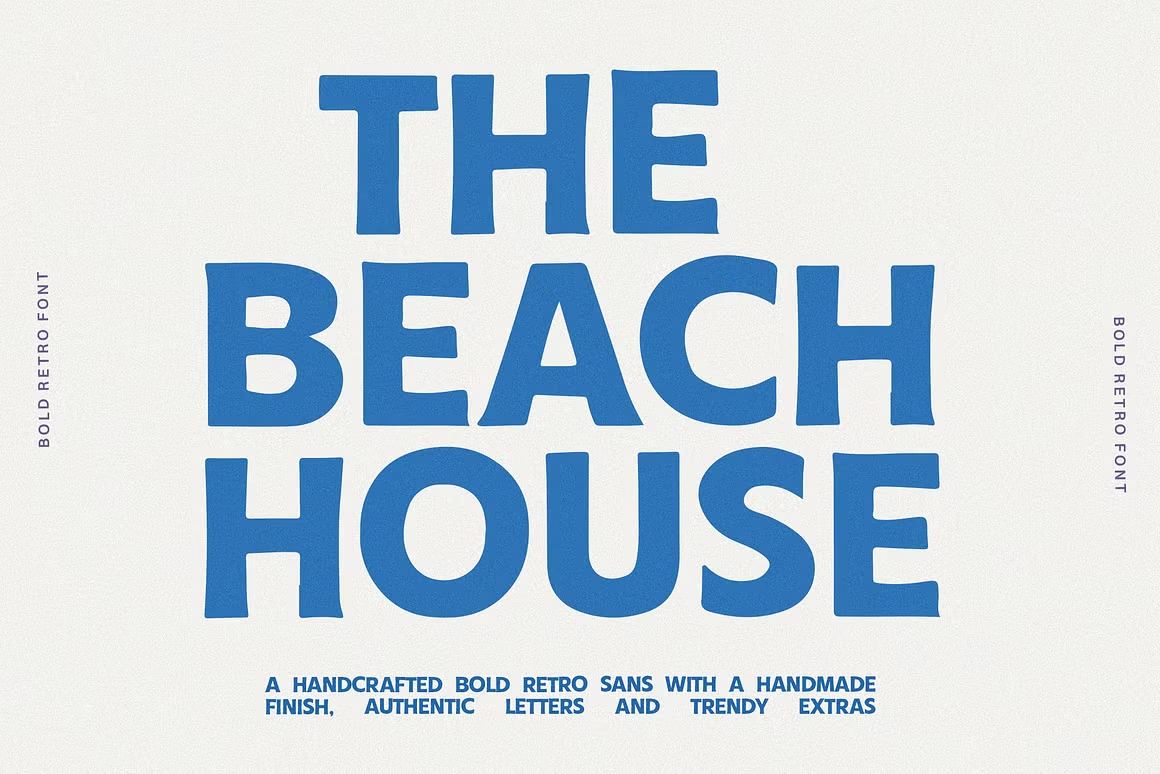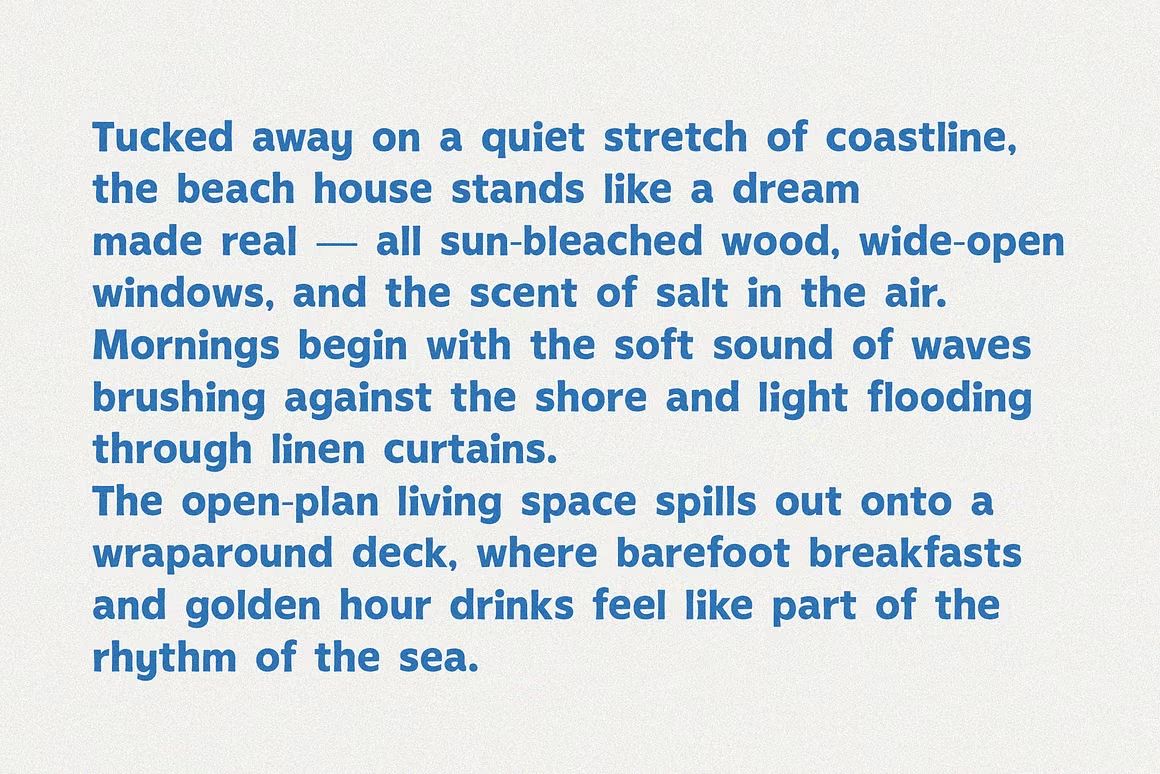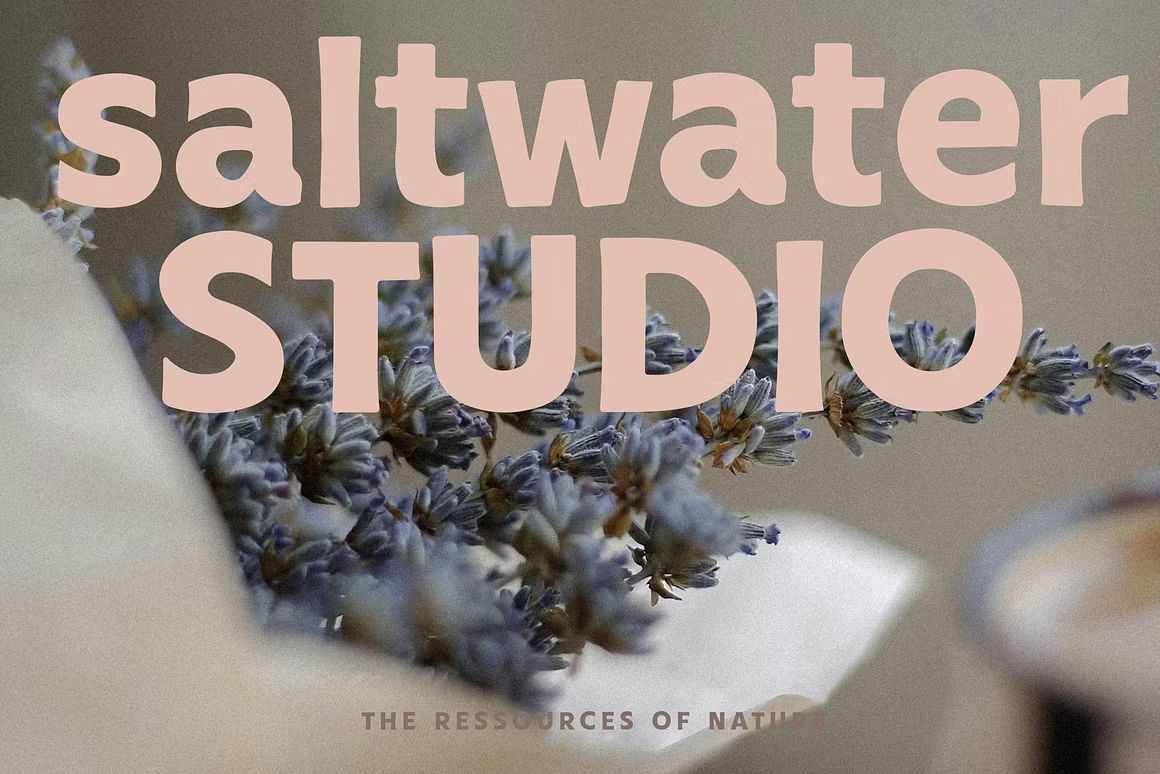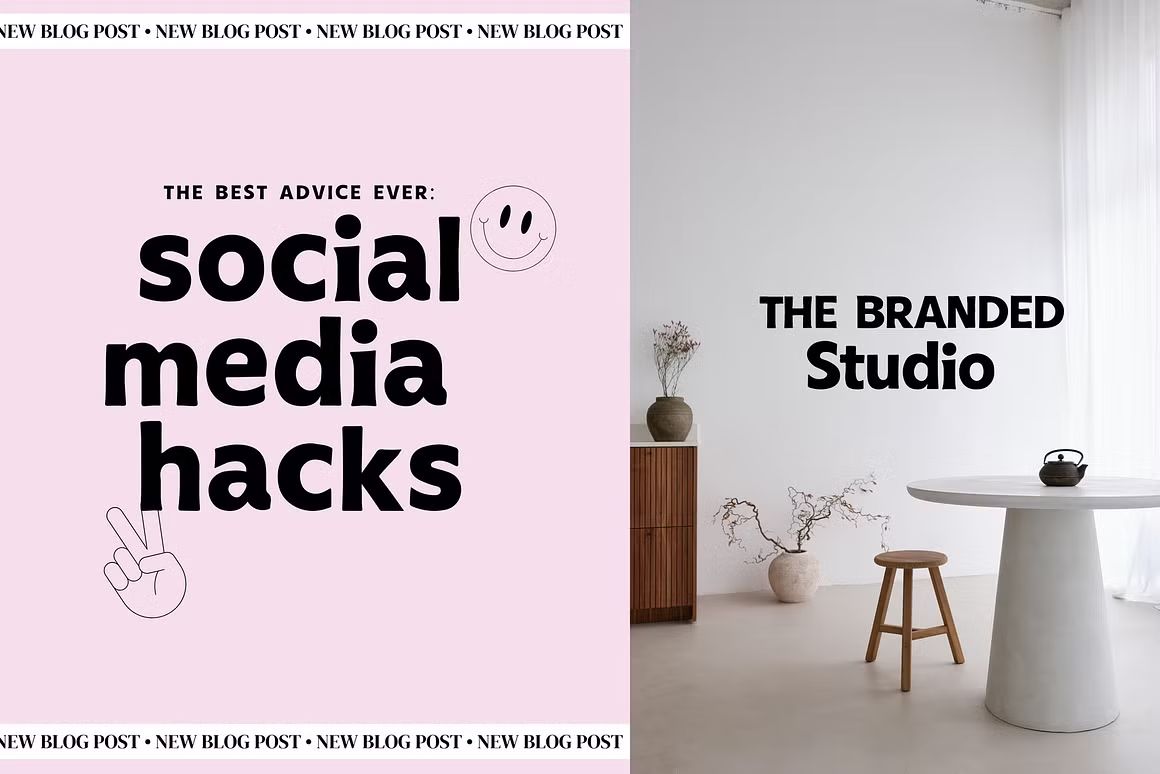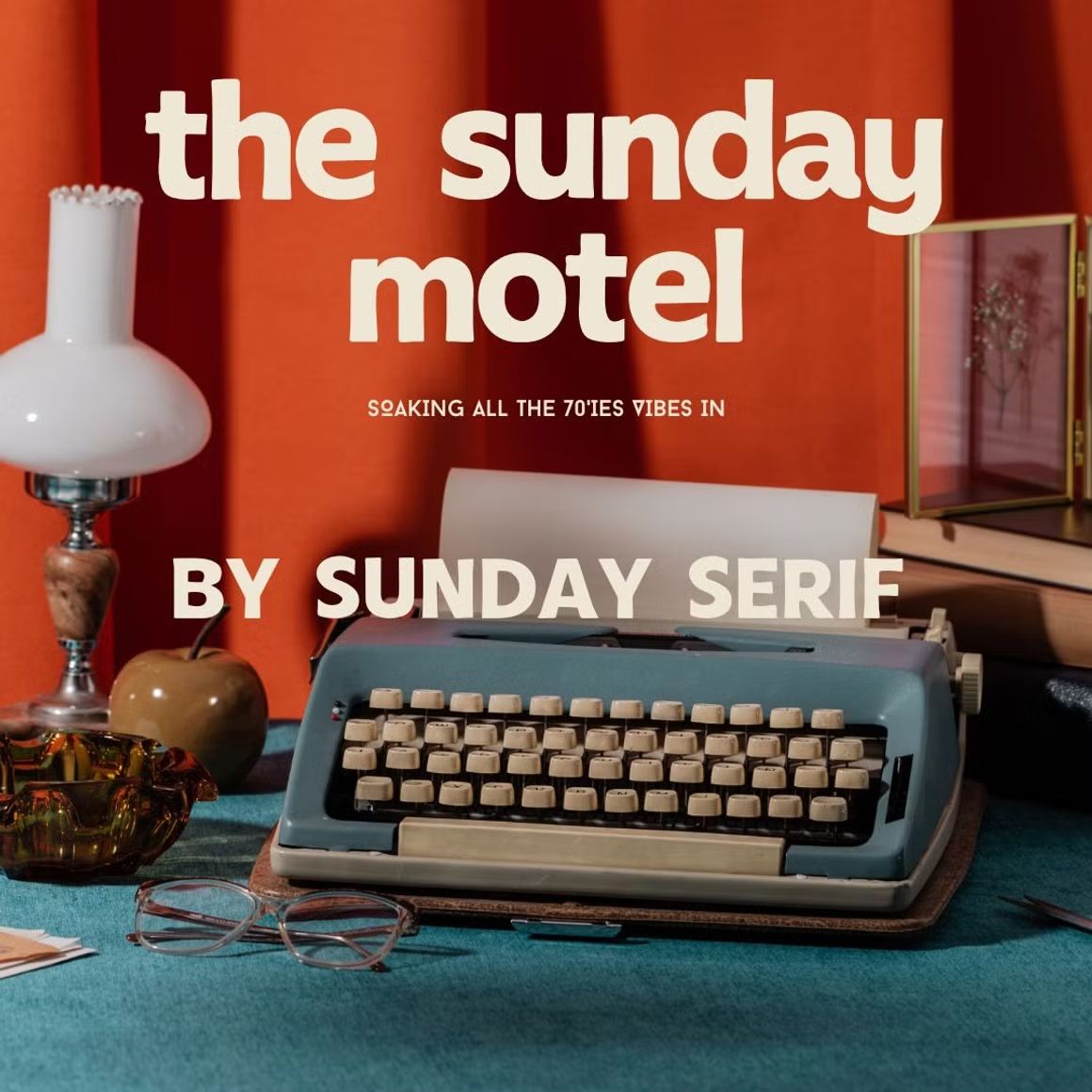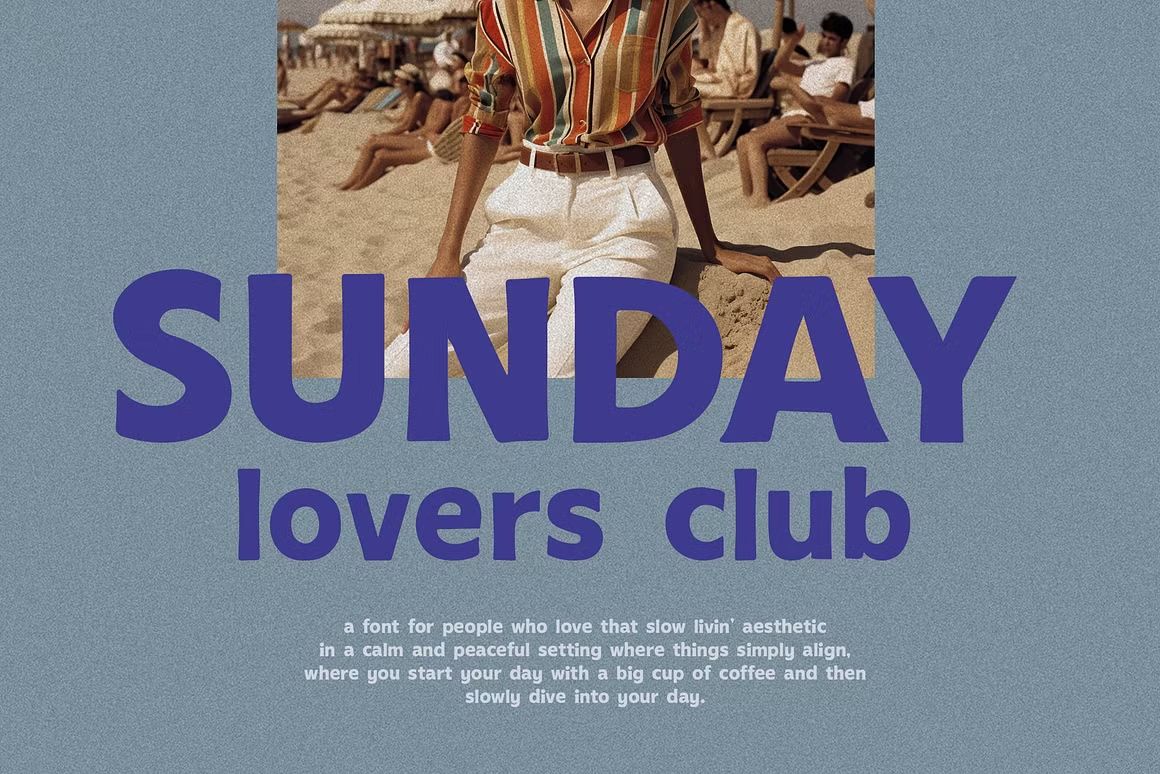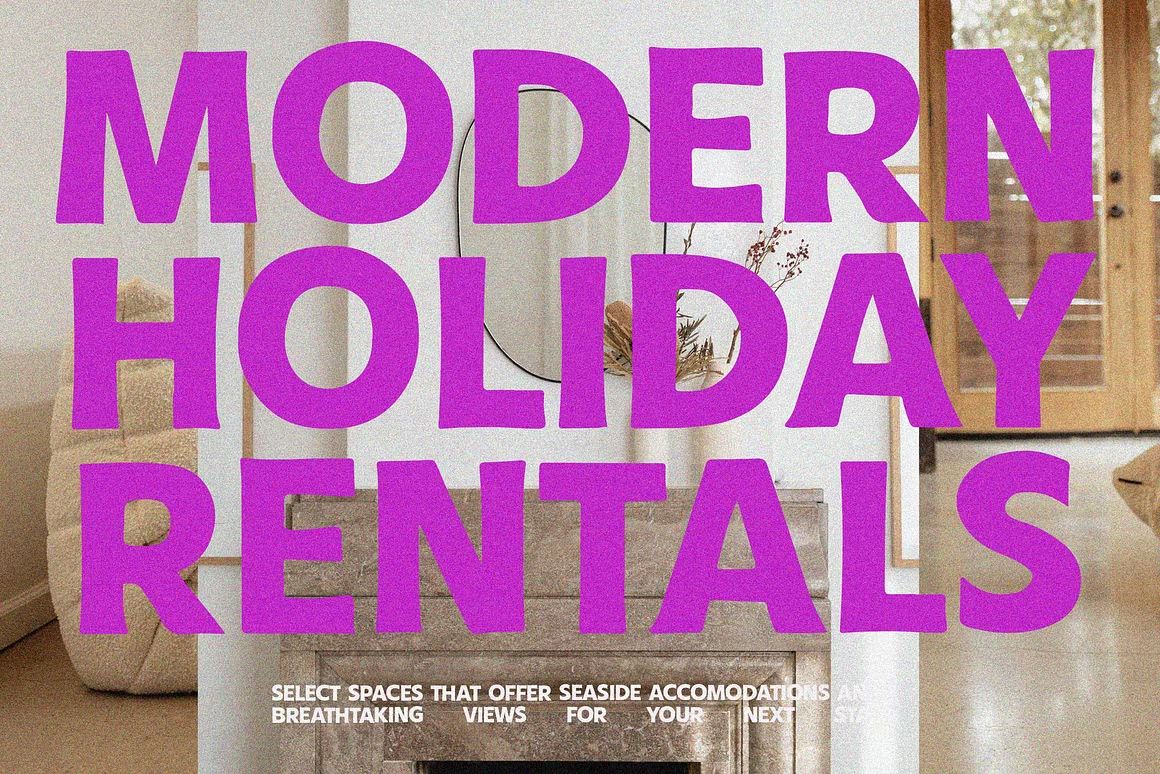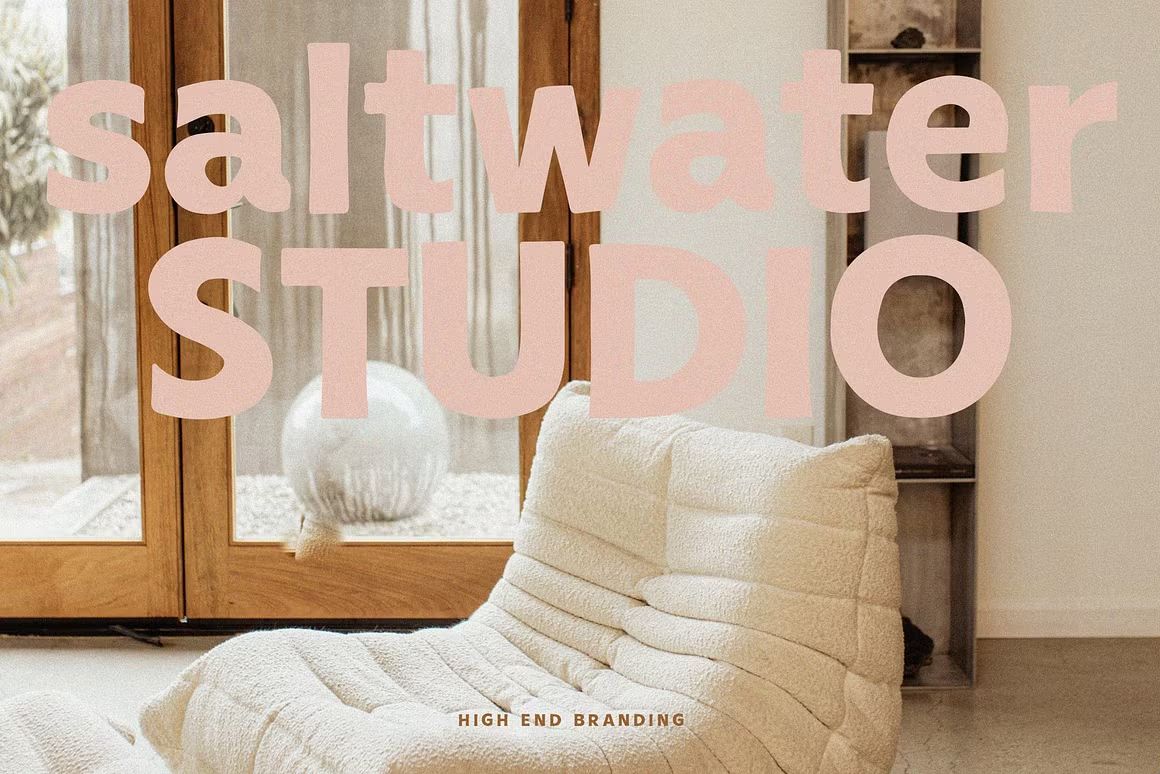
Beach House – Bold Sans Serif Font
Beach House adalah font sans serif tebal dengan gaya modern dan kasual, cocok untuk desain poster, branding, kemasan, dan proyek kreatif yang ingin tampil mencolok dan santai.
Beach House adalah font sans serif bold dengan tampilan modern dan kasual yang dirancang untuk menarik perhatian. Dengan bentuk huruf yang kuat dan bersih, font ini sangat cocok digunakan untuk poster, branding, kemasan produk, dan berbagai proyek desain yang ingin menonjolkan kesan santai namun tetap profesional.
Fitur unggulan:
• Gaya sans serif tebal dengan tampilan modern dan kasual
• Cocok untuk poster, branding, kemasan, dan media sosial
• Termasuk huruf besar, huruf kecil, angka, dan simbol
• Ideal untuk proyek digital maupun cetak yang membutuhkan tampilan mencolok dan stylish